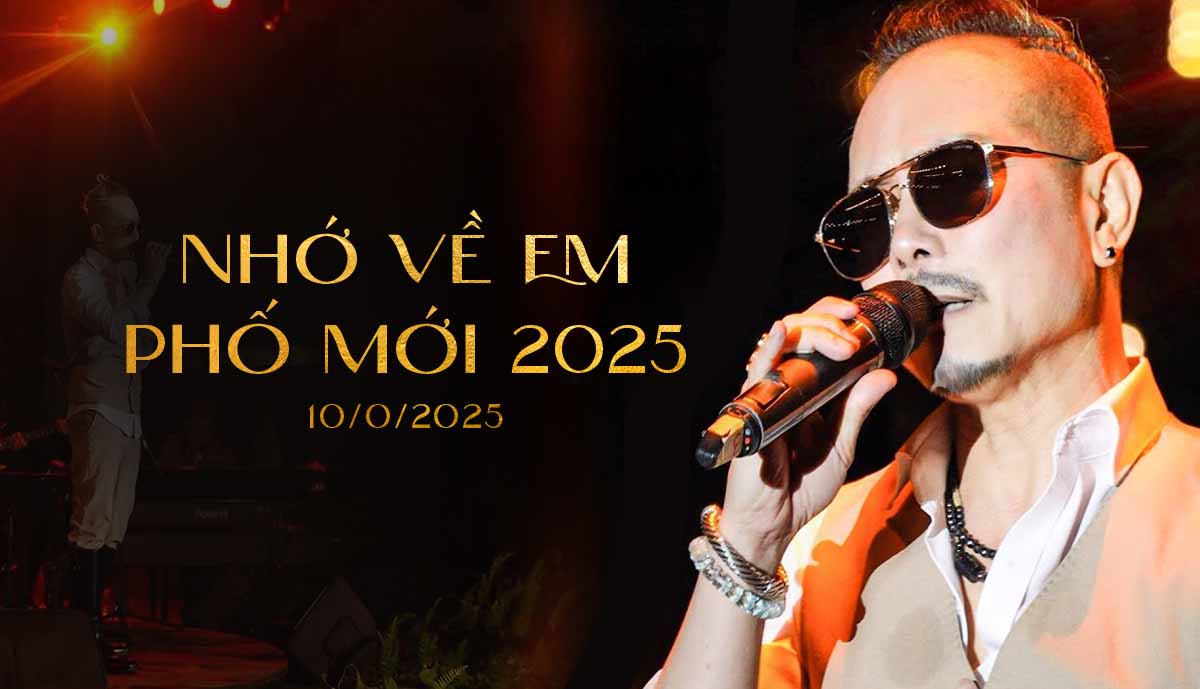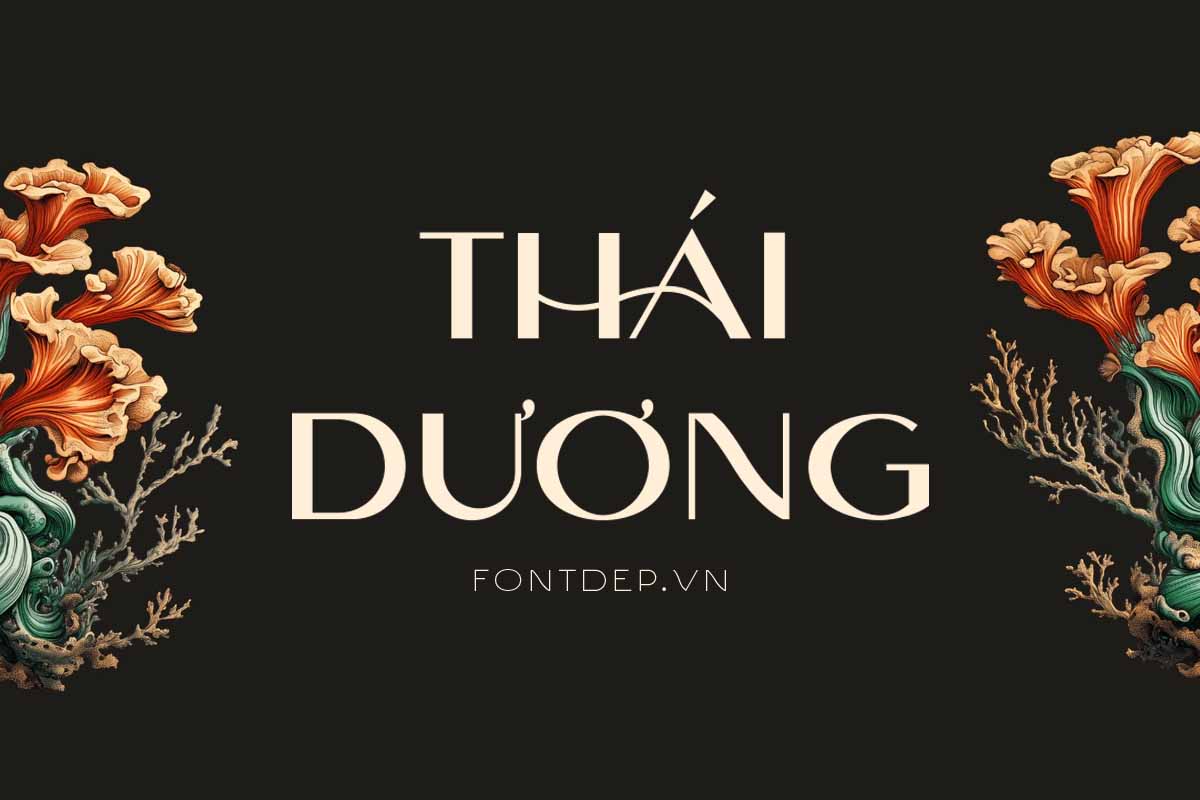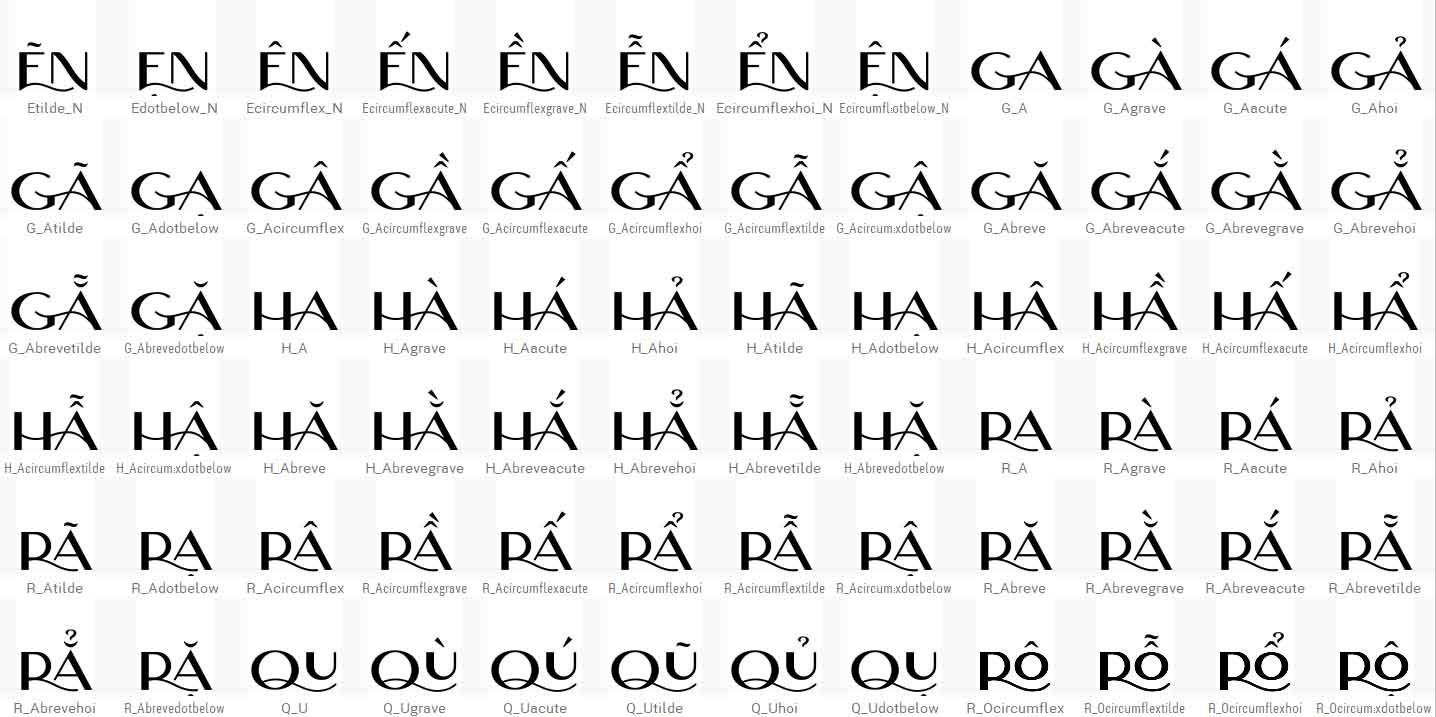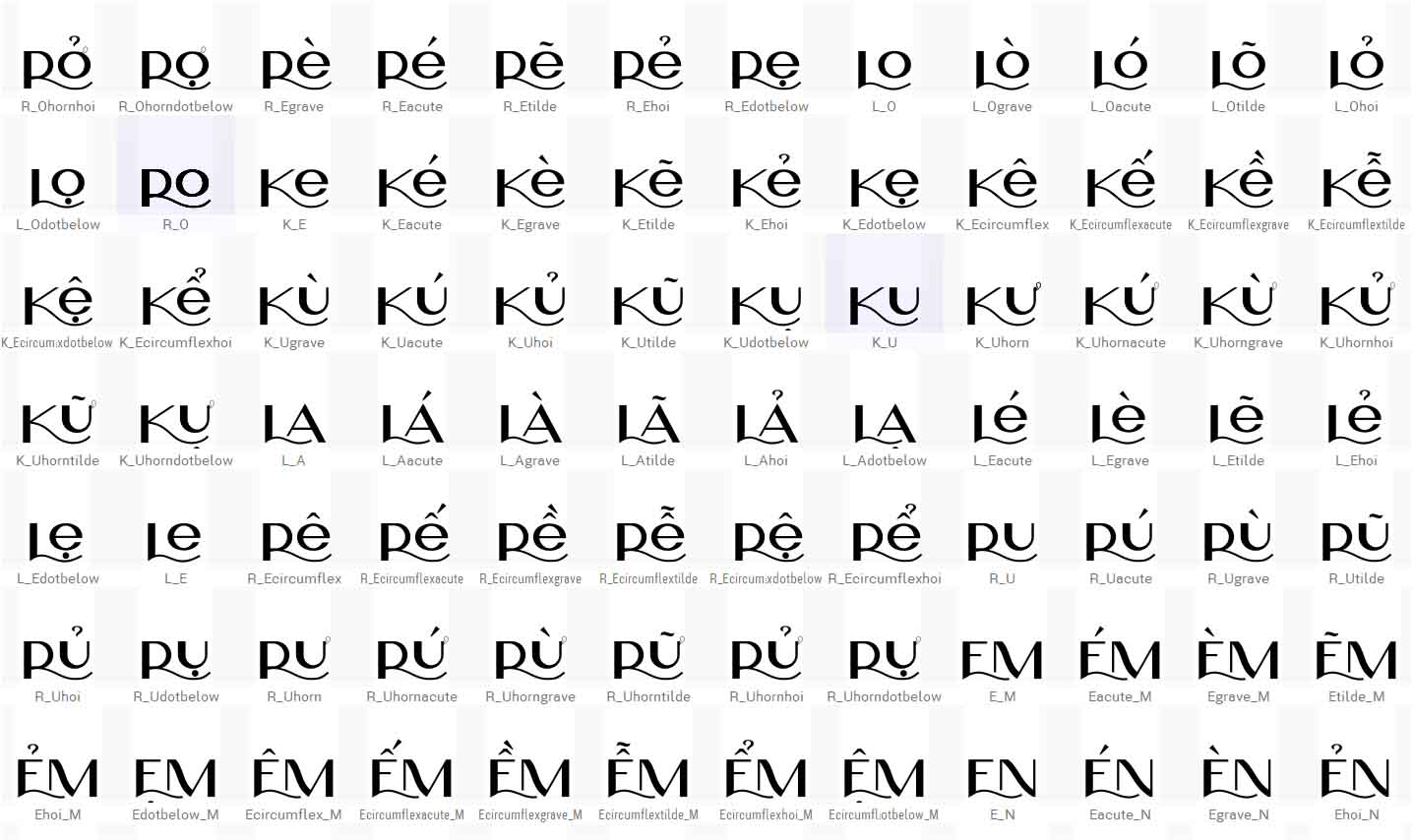
Font TH Cameo Sans – Kiểu Chữ Không Chân Việt Hóa Thanh Lịch, Hiện Đại
TH Cameo Sans là một bộ font sans-serif hiện đại đã được Việt hóa bởi nhóm thiết kế S99.vn. Kiểu chữ này gây ấn tượng bởi sự tối giản, thanh thoát và dễ đọc, phù hợp với xu hướng thiết kế thương hiệu hiện nay.
Với các đường nét không chân, đều đặn, TH Cameo Sans giúp văn bản hiển thị rõ ràng trên cả màn hình kỹ thuật số lẫn bản in. Các chữ cái được thiết kế với độ rộng vừa phải, cân đối và dễ nhận diện. Đặc biệt, phiên bản Việt hóa đã được tinh chỉnh kỹ phần dấu tiếng Việt – đảm bảo dấu thanh (sắc, huyền, hỏi, ngã, nặng) hiển thị chuẩn xác, không bị lệch hay dính, kể cả trong đoạn văn dài.
Ứng dụng thực tế của font này rất đa dạng: từ thiết kế logo spa, mỹ phẩm cao cấp, đến tạp chí, danh thiếp, tiêu đề website hoặc brochure thương hiệu. TH Cameo Sans mang lại cảm giác chuyên nghiệp nhưng thân thiện, giúp tăng độ tin cậy và tính thẩm mỹ cho thương hiệu.